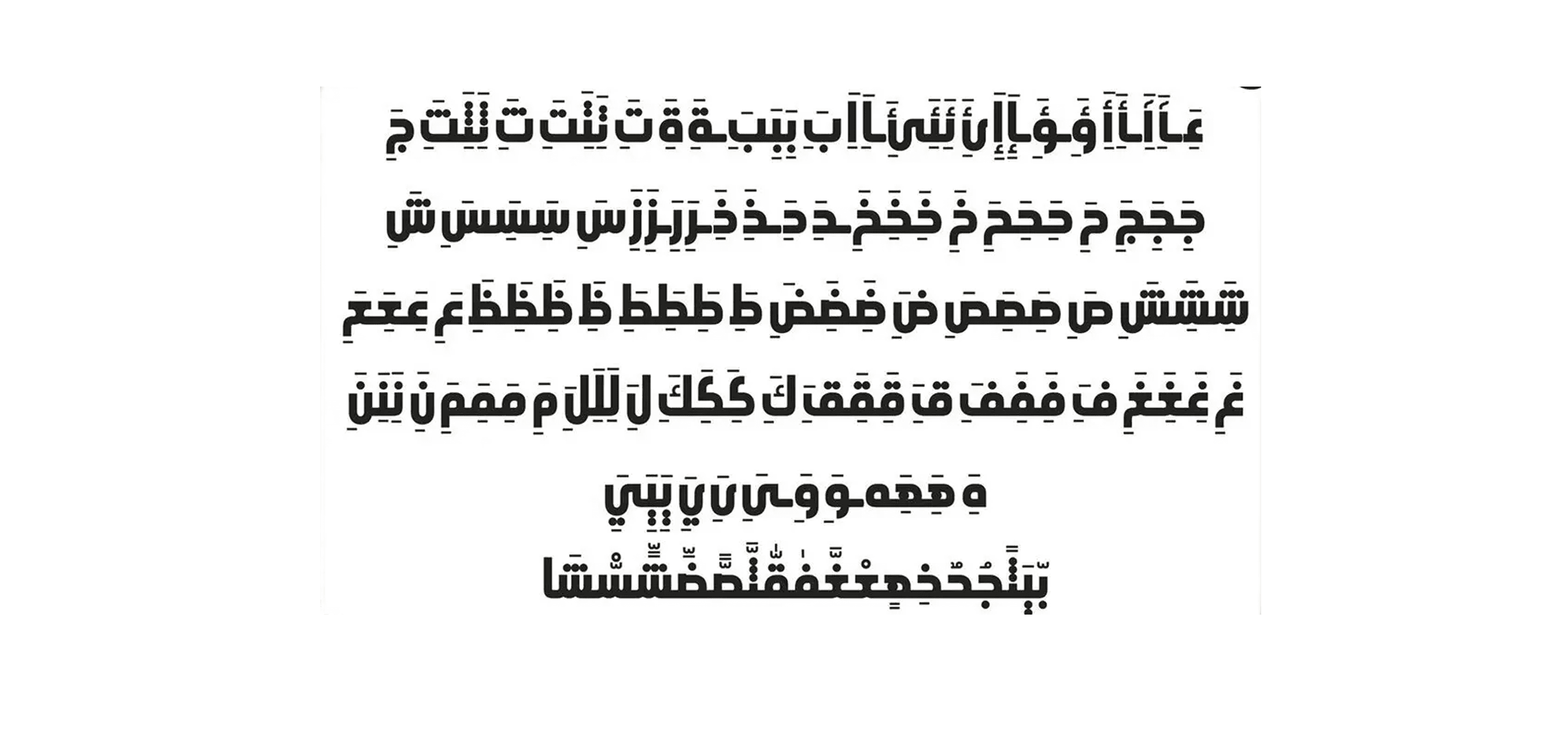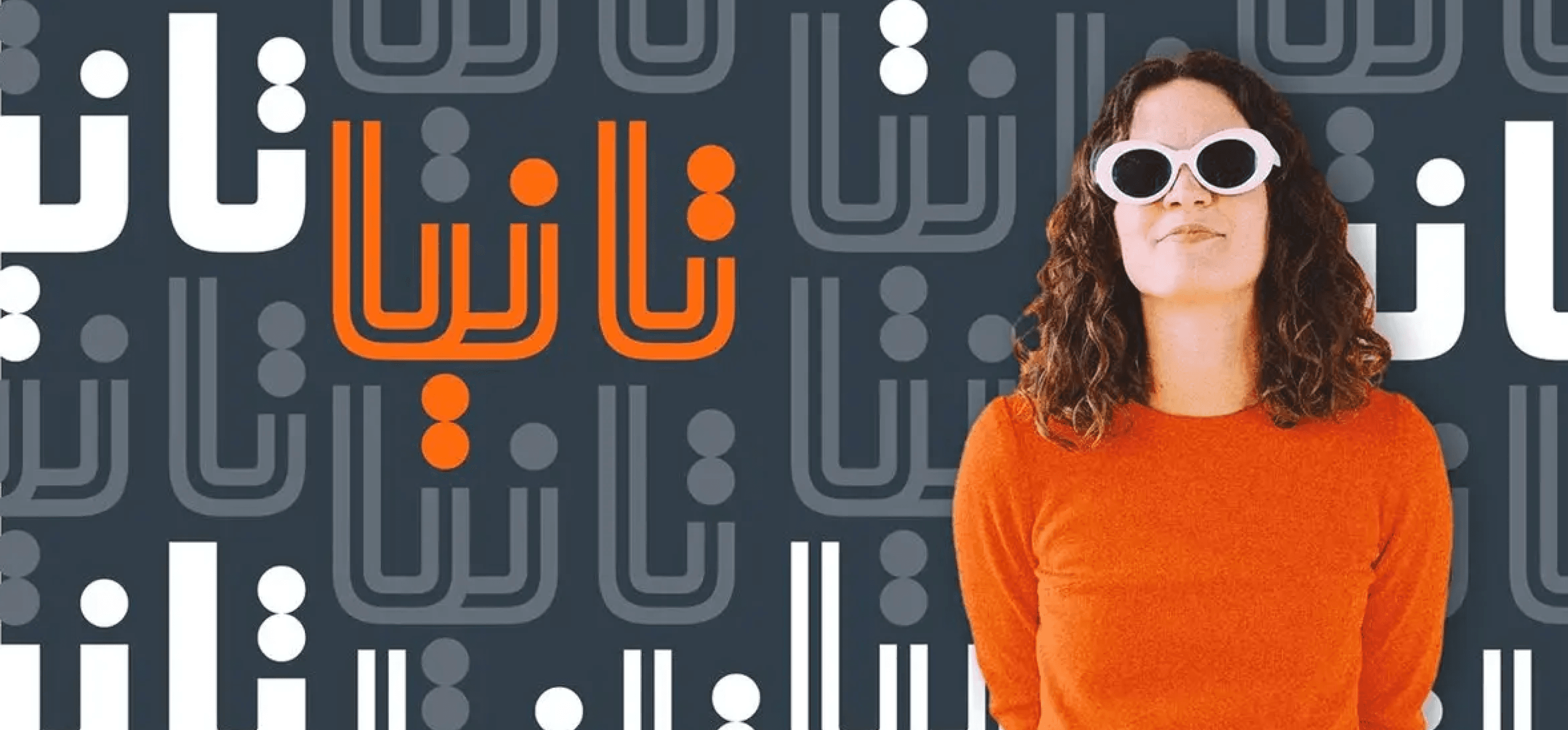
الخط "JH Tania 2x" هو خط هندسي، يتضمن وزنين: أحدهما بخط مزدوج والآخر بخط أسود (غامق). يتميز بتصميم عصري مثالي للاستخدام في الشعارات، العلامات التجارية، والعناوين.